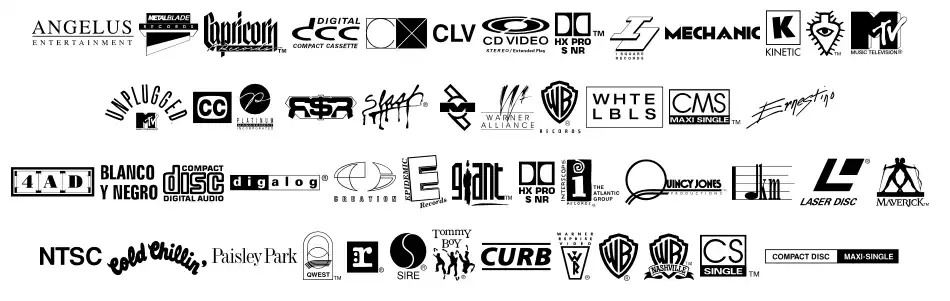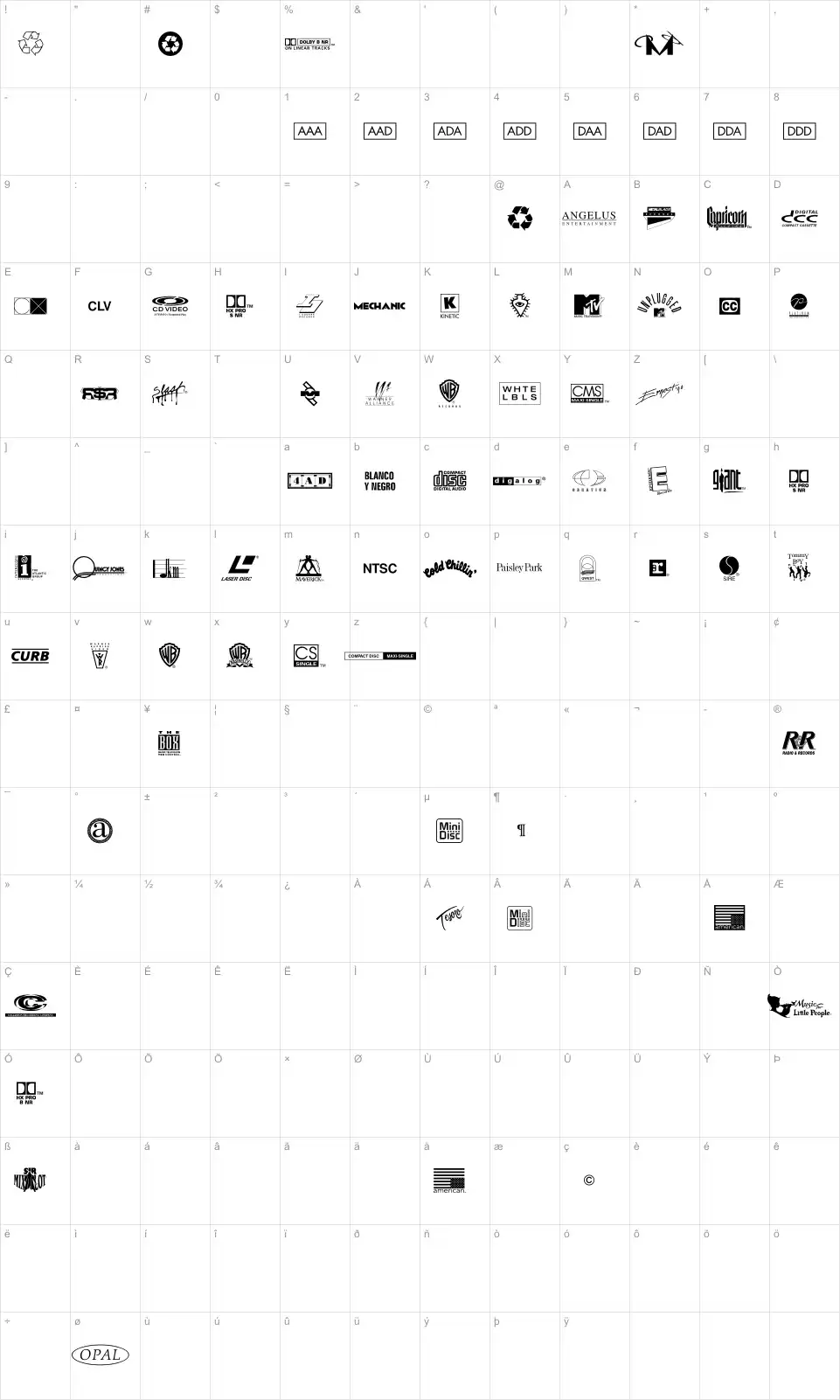
Warner Logo Font Nine – Download Grátis
A Warner Logo Font Nine é uma fonte Dingbats criada especialmente para representar logos e símbolos. Desenvolvida pelo mesmo designer, esta font é perfeita para quem busca um visual atraente e diferenciado para seus projetos gráficos, seja em logomarcas, sinais ou qualquer outro elemento visual. Com a Warner Logo Font Nine, você pode criar texturas interessantes e personalizar textos de forma única, sem precisar de grandes conhecimentos de design. Esta font vem em formato TTF, o que significa que pode ser usada em qualquer sistema de texto. Adicionada em julho de 2022, a font já foi baixada 6736 vezes. Com um tamanho de arquivo de apenas 90 KB, a Fonte Warner Logo é uma ótima opção para quem precisa de um elemento visual atraente sem comprometer os recursos de armazenamento.